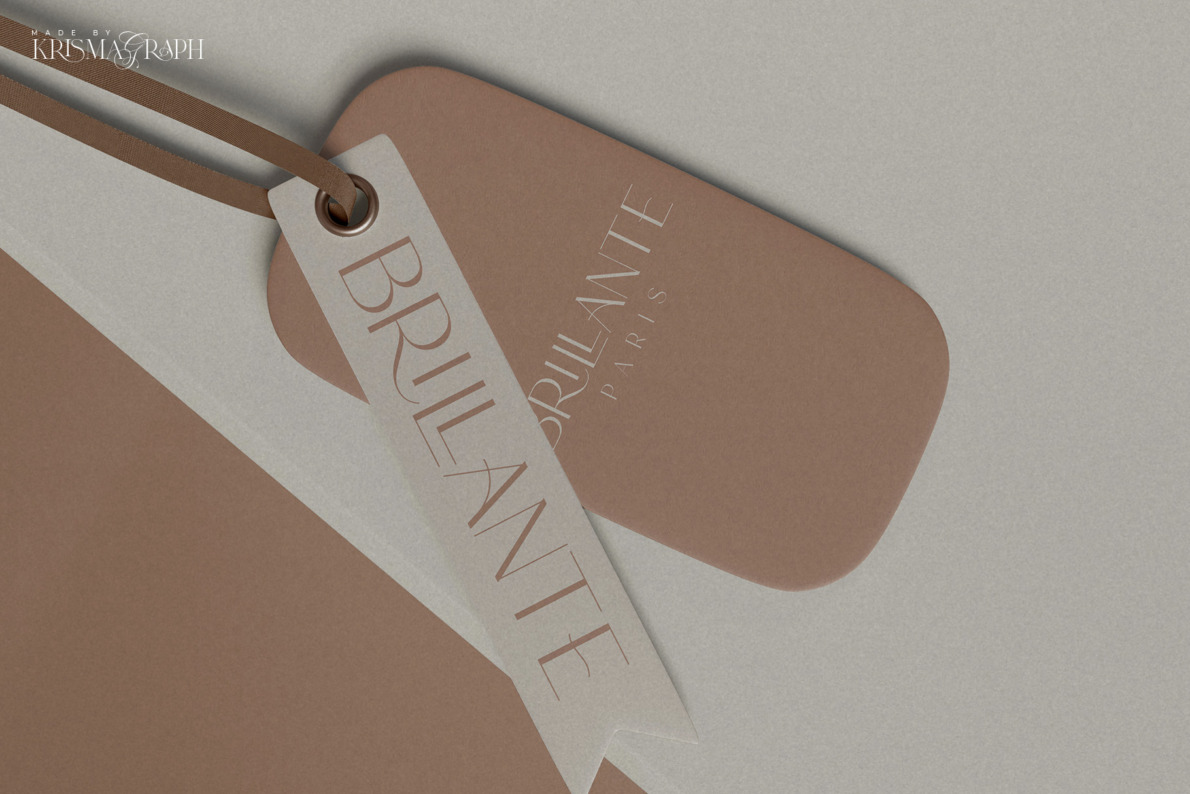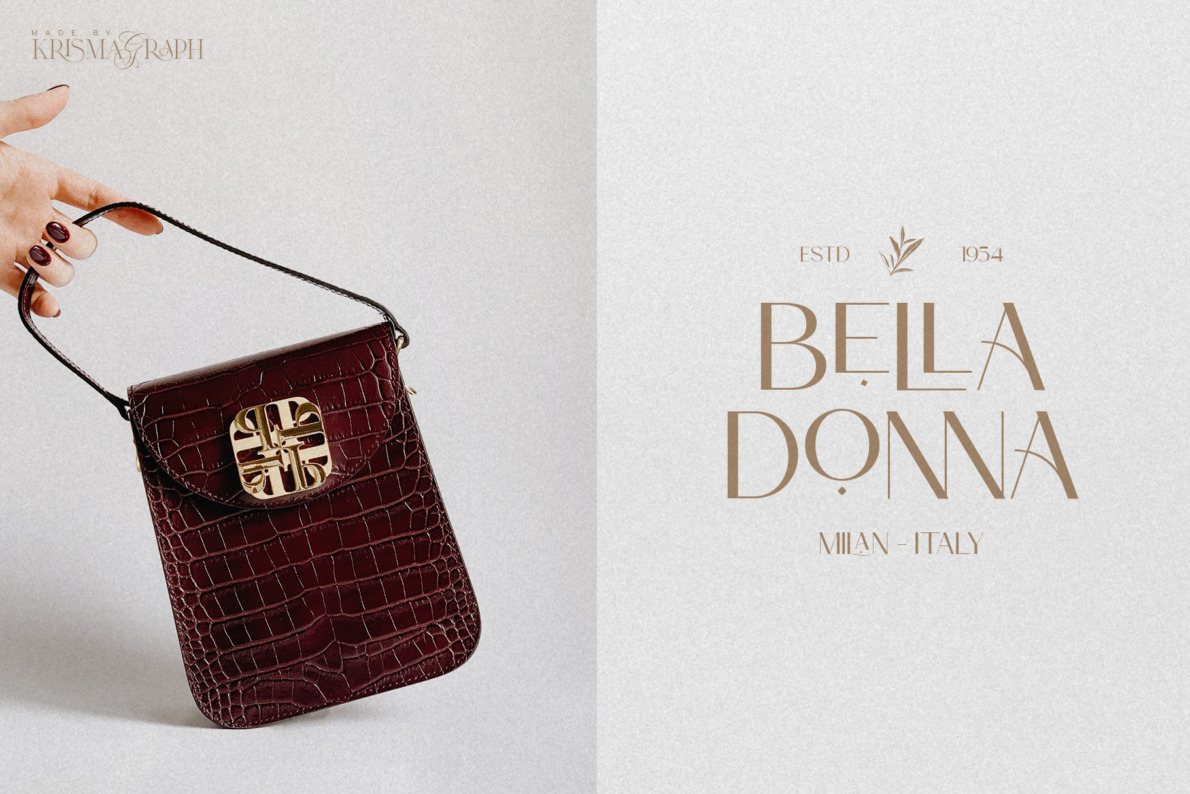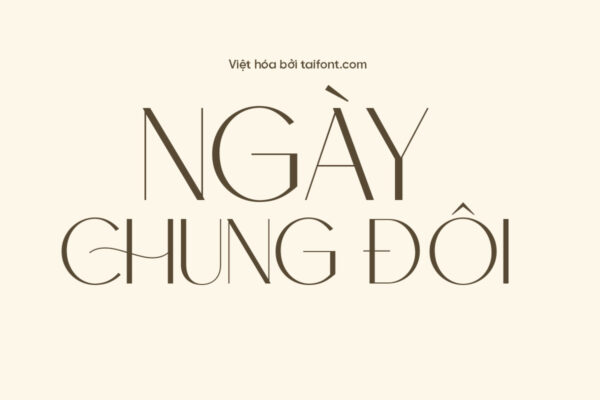
Giới thiệu về Font TF Eternal Spring Việt hóa
TF Eternal Spring Việt hóa là một font chữ không chân (sans-serif) nổi bật với thiết kế thanh mảnh, tinh tế và đầy nữ tính, gợi cảm giác về sự mềm mại, lãng mạn và sự tươi mới của mùa xuân vĩnh cửu. Font này toát lên phong thái nhẹ nhàng, duyên dáng và sang trọng, lý tưởng để tạo điểm nhấn tinh tế và thu hút mọi ánh nhìn trong các thiết kế đòi hỏi sự thanh lịch và quyến rũ.
Với đặc điểm là nét không chân thanh mảnh, tính thẩm mỹ cao và phong thái nữ tính, Eternal Spring là lựa chọn hoàn hảo cho các ấn phẩm cần sự sang trọng và khác biệt, đặc biệt là trong các lĩnh vực:
- Thiết kế thiệp cưới: Hoàn hảo để viết tên cô dâu chú rể, lời mời, hoặc các thông tin chi tiết trên thiệp cưới, menu tiệc, bảng tên khách mời. Nét chữ thanh lịch và duyên dáng sẽ biến mỗi tấm thiệp thành một tác phẩm nghệ thuật, mang đậm dấu ấn cá nhân và sự lãng mạn, trang trọng cho ngày trọng đại.
- Thiết kế thiệp mời: Lý tưởng để viết lời mời trang trọng cho các sự kiện đặc biệt, tiệc tùng, khai trương hoặc các buổi lễ. Font này sẽ làm cho mỗi tấm thiệp trở nên độc đáo, cao cấp và đầy thu hút.
- Thiết kế thời trang: Phù hợp cho các thương hiệu thời trang cao cấp, đặc biệt là thời trang nữ. Font này có thể được sử dụng cho logo, nhãn mác sản phẩm, lookbook, hoặc các chiến dịch quảng bá bộ sưu tập. Eternal Spring giúp truyền tải vẻ đẹp thanh lịch, đẳng cấp và độc đáo của trang phục, nâng tầm giá trị thương hiệu.
- Thiết kế mỹ phẩm và nước hoa: Lý tưởng cho bao bì, nhãn hiệu hoặc các ấn phẩm quảng cáo muốn truyền tải sự tinh tế, nữ tính và sang trọng.
Với TF Eternal Spring Việt hóa, bạn có thể dễ dàng thổi hồn tinh tế, sang trọng và vẻ đẹp hoàn hảo vào các thiết kế, tạo ra những sản phẩm không chỉ đẹp mắt mà còn đầy cảm xúc và sức hút đặc biệt.
Font Việt hóa TF Eternal Spring – Nhiều glyphs